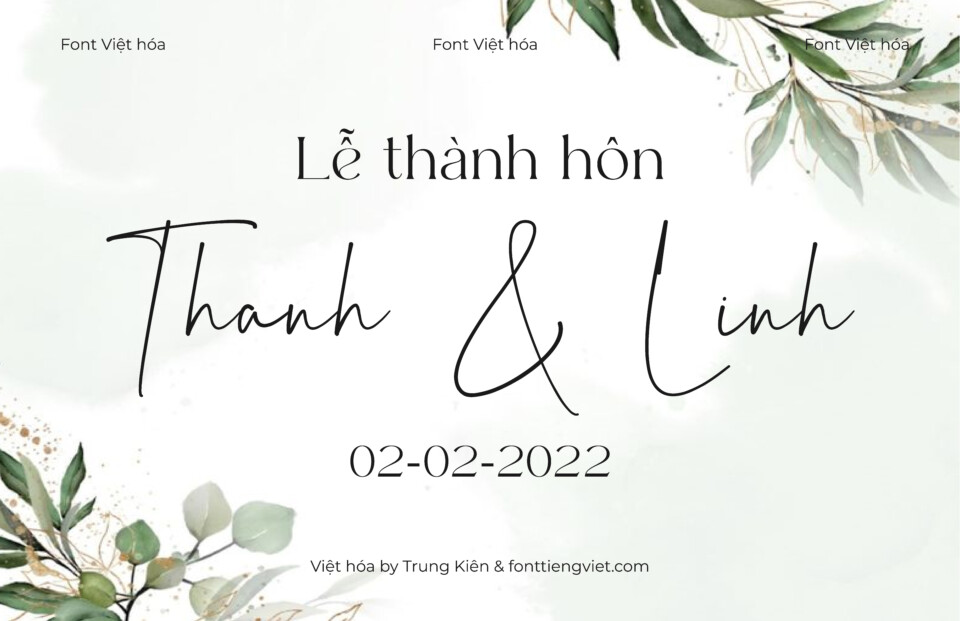
Font Việt hóa 1FTV VIP Katty Diona – Font thiệp cưới sang trọng và tinh tế
Giới thiệu về Font Việt hóa 1FTV VIP Katty Diona – Font thiệp cưới
Trong thiết kế đồ họa hiện nay, việc lựa chọn một Font Chữ phù hợp đóng vai trò then chốt tạo nên linh hồn cho tác phẩm. Font Việt hóa 1FTV VIP Katty Diona – Font thiệp cưới là một bộ phông chữ thuộc phong cách Script hiện đại, mang hơi hướng bay bổng và lãng mạn. Với các đường nét thanh mảnh, uốn lượn mềm mại, bộ font này cực kỳ phù hợp cho các mục đích thiết kế yêu cầu tính thẩm mỹ cao như thiệp mời, bìa sách hay các ấn phẩm kỷ niệm. Đặc biệt, phiên bản Việt hóa giúp người dùng sử dụng thuận tiện mà không lo lỗi dấu tiếng Việt.
Đặc điểm nổi bật của font chữ Katty Diona
Bộ Font Việt hóa 1FTV VIP Katty Diona – Font thiệp cưới sở hữu các ký tự thay thế (alternates) và dấu gạch nối (ligatures) vô cùng đa dạng. Điều này cho phép người thiết kế tự do sáng tạo, tạo nên những dòng văn bản mang đậm dấu ấn cá nhân. Độ tương phản giữa các nét thanh và nét đậm được căn chỉnh hoàn hảo, giúp font chữ không chỉ đẹp mắt mà còn rất dễ đọc trên nhiều chất liệu in ấn khác nhau.
Ứng dụng thực tế của Font Việt hóa 1FTV VIP Katty Diona
Nhờ vẻ đẹp sang trọng, bộ font này thường xuyên được ưu tiên trong thiết kế thiệp cưới, menu nhà hàng cao cấp và các thương hiệu thời trang. Ngoài ra, giáo viên và học sinh cũng có thể sử dụng để trang trí báo tường hoặc các slide thuyết trình cần sự trang nhã. Việc cài đặt font rất đơn giản, tương thích tốt với các phần mềm phổ biến như Photoshop, Canva hay Microsoft Word, giúp bạn tiết kiệm thời gian tối đa.